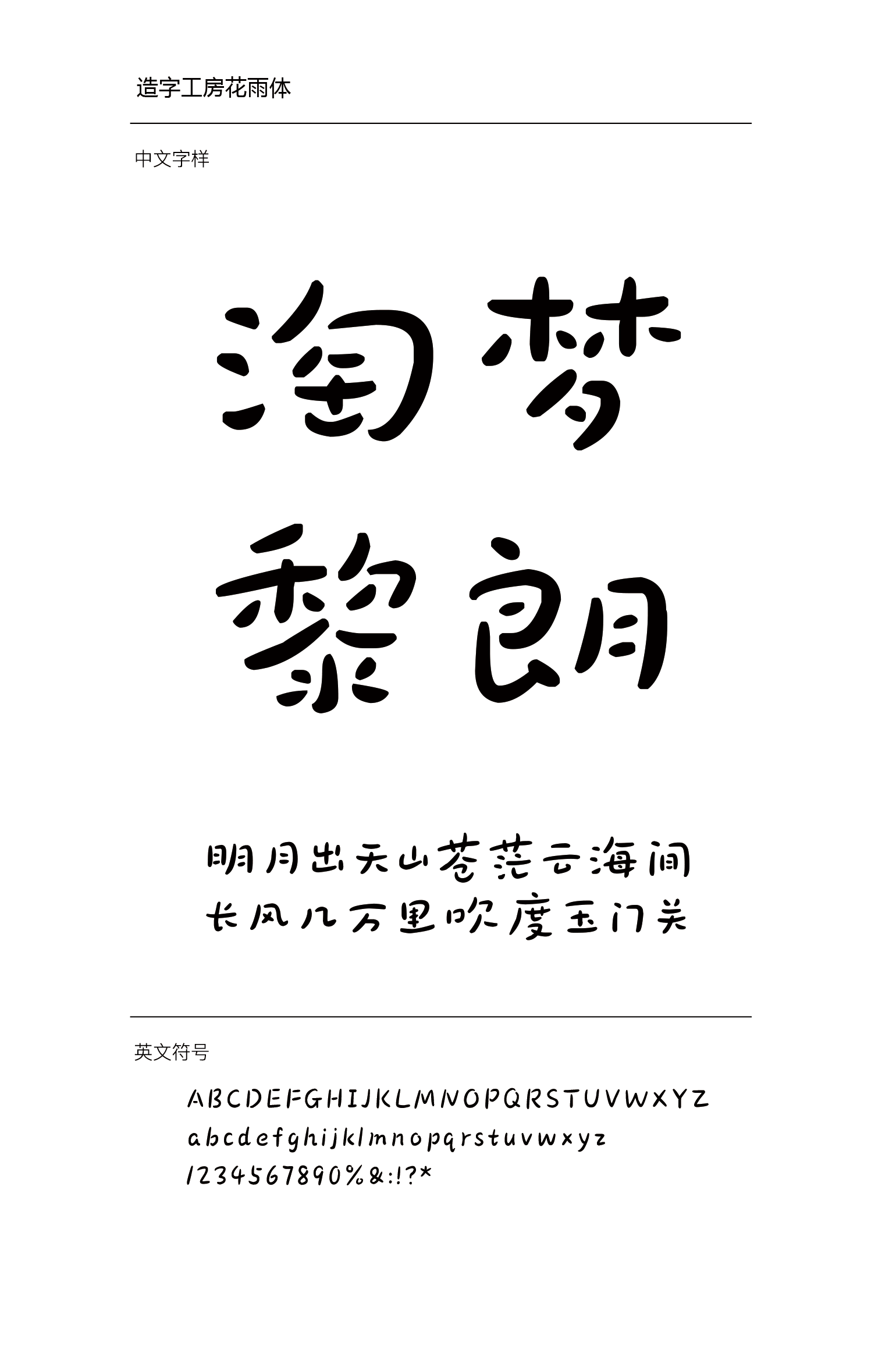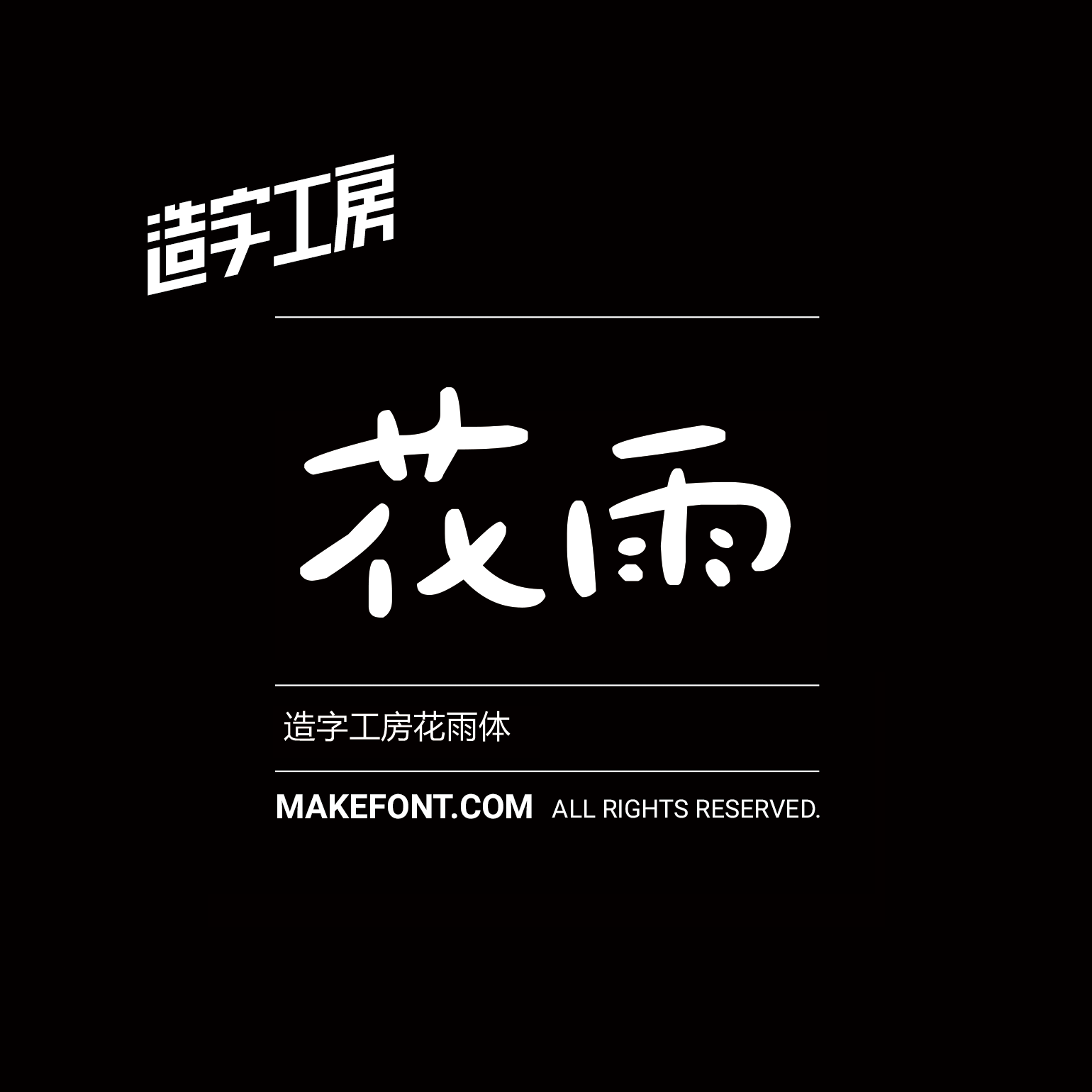
造字工房花雨体设计说明
造字工房花雨体是一款小清新风格的手写体。笔画自然流畅,突出了字体的松弛感。字体结构优美灵动,风格清新,层次丰富赏心悦目。本字体为简体字库,采用OpenType/CID格式,Adobe-GB1-5编码。基于中华人民共和国GB2312-80字符集标准,另按需添加101个汉字。共收容字数6864CJK汉字,ASCII常用字符100个。